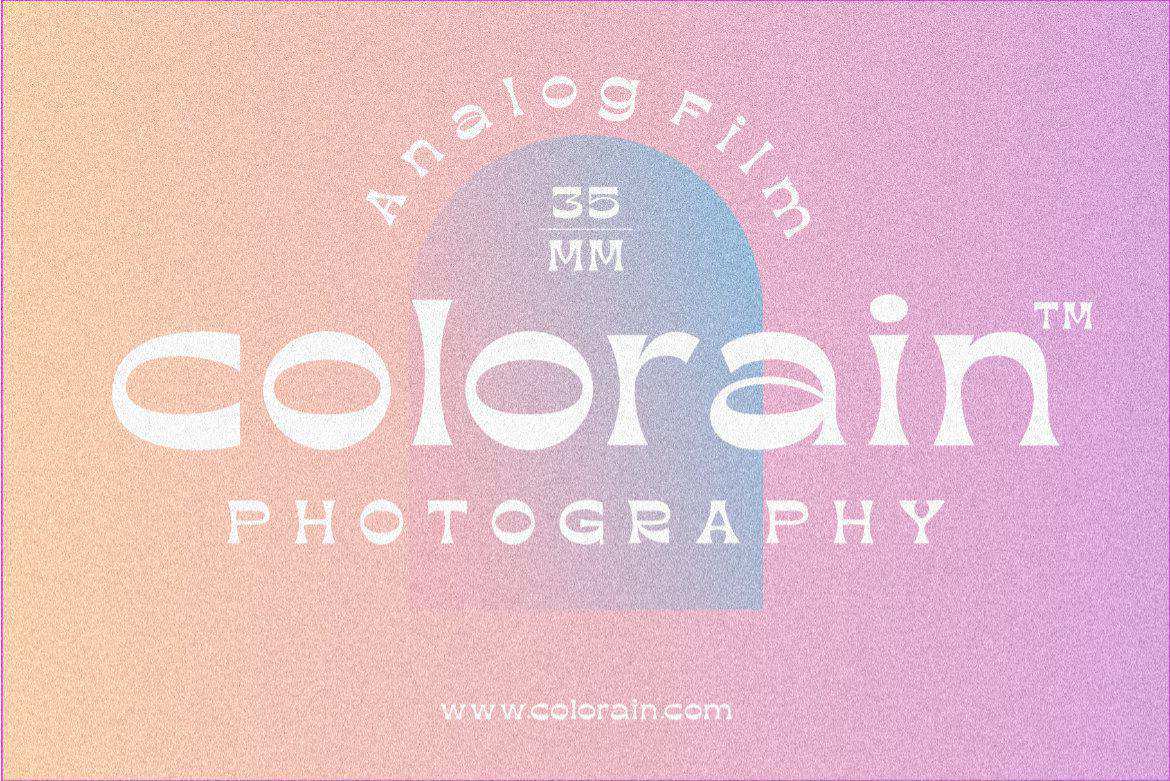
Megar是一个显示字体,具有两种样式,常规和倾斜。它可以用一个房间的主题来完成您的工作。MegarisSoldataAffordable价格和您将获得很多Bonus Background渐变和渐变形状。立即获取此字体!此产品包括:Megar Isa Display Font,具有可追溯的外观,可提供2种样式,常规和斜形。它可以用一个区域零件主题来完成您的工作。MegarisSoldAtafordable价格,您将获得很多Bonus Background Gradient和gradientshapes。立即获取此Font!该产品包括: